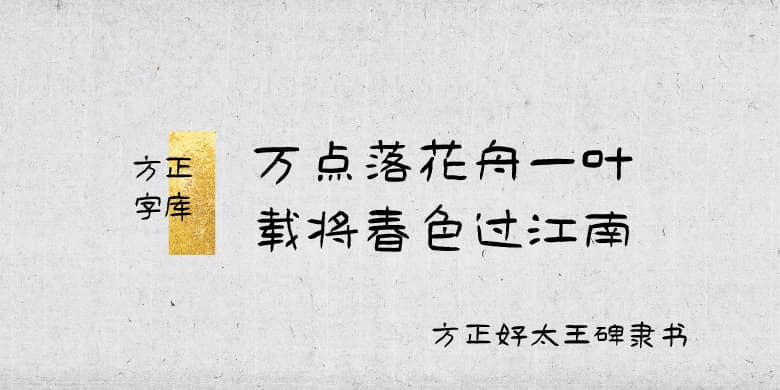
品牌:方正字库中华精品字库设计师:肖文经发行时间:2021字库编码:大陆简体(GB2312-80)分类:常规书写·毛笔字体属性:精品字
关于好太王碑:
中国东晋时期高句丽第20代王长寿王为其父亲第19代王谈德所立记功碑。碑文涉及高句丽建国传说、好太王功绩及当时东北、朝鲜半岛与日本列岛倭人之间的关系,为中外学者所珍视。
字体特征:
字体以《好太王碑》为临创开发依据,较好继承了好太王碑结字的开张疏朗,结构的恢弘平实,笔画线条的雄强厚重、朴茂沉稳的特点,字体稚拙真率的意趣浓厚。
应用场景:
临创者:肖文经
整理/设计:梅花、关秋培、刘昱程、刘聪、卫欢欢、邵维、冯红晨、田玄丹、孙睿、高茜、王军芳、杨颖
审稿专家:刘洪彪、李有来、朱培尔、虞晓勇、邵佩英、张志庆、仇寅